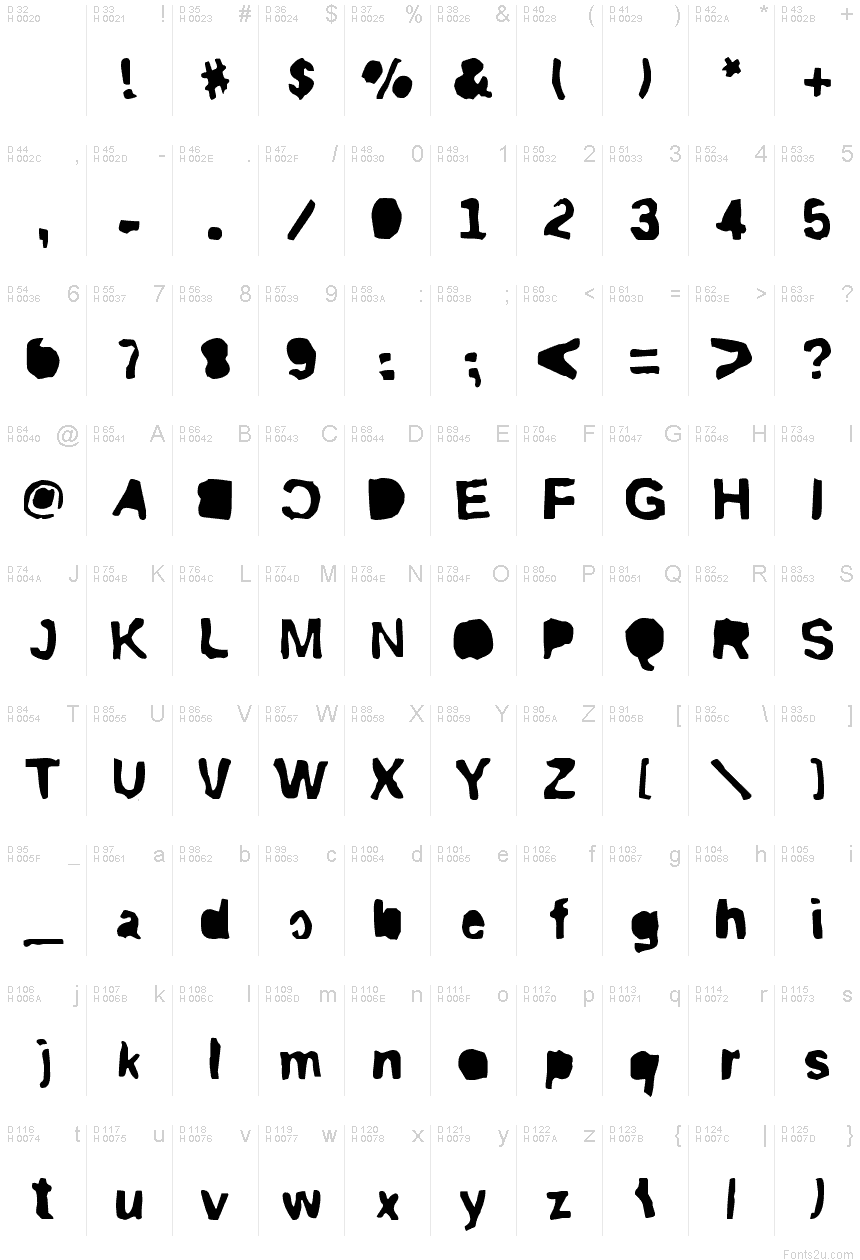
rip TRASH Round Mirror, entworfen von Manuel Viergutz, ist eine kostenlose, grob geschnittene Display-Schrift mit dichten, unregelmäßigen Buchstabenformen. Die Striche schwellen unvorhersehbar an und ab, und die unebenen Außenkanten erinnern an Buchstaben, die aus schwerem Papier ausgeschnitten wurden. Abgerundete Ecken mildern die ansonsten rohe Silhouette.
Punk- und DIY-Grafiken passen am besten dazu; die verzerrten Formen eignen sich für Musikplakate, Albumcover, Skate-Merchandise und handgemachte Event-Flyer. Sie richtet sich direkt an Underground-Labels, Bands und jugendorientierte Veranstaltungen, die Beschriftungen mit einer handgemachten Note suchen.
rip TRASH
- Styles: regular, mirror, cut, cutMIRROR, round, roundMIRROR